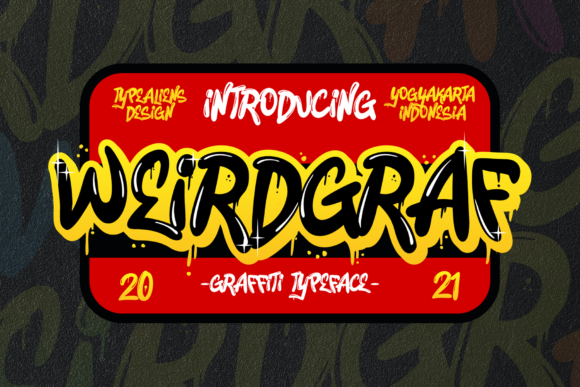
Creativefabrica Weirdgraf Font
[Creativefabrica] Weirdgraf Font
Weirdgraf - это крутой, веселый, урбанистический шрифт.
Вдохновленный граффити, этот шрифт сделает каждое ваше творение модным и интересным. Добавьте его уверенно в свои проекты, и вам понравится результат.